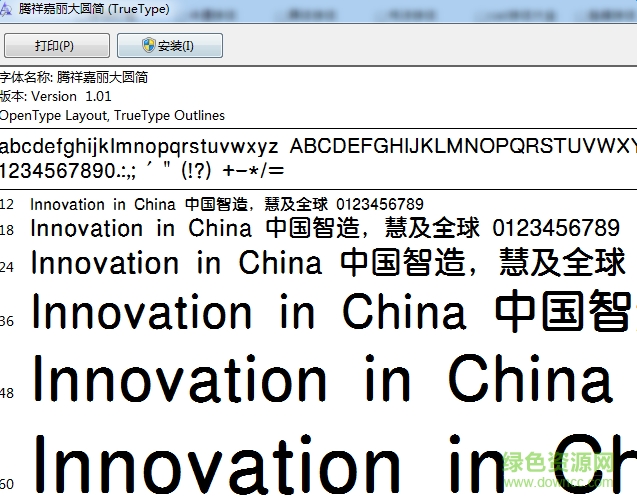
騰祥嘉麗大圓簡(jiǎn)字體是一款超好用的個(gè)性簡(jiǎn)體中文字體,該字體能夠更好的滿足設(shè)計(jì)行業(yè)的需要,使用戶的廣告更具特色,有需要的朋友可以免費(fèi)下載收藏。
騰祥嘉麗大圓簡(jiǎn)字體是一款極具個(gè)性的字體,該字體十分飄逸,彰顯了自己的個(gè)性,有喜歡的朋友可以來綠色資源網(wǎng)下載使用!